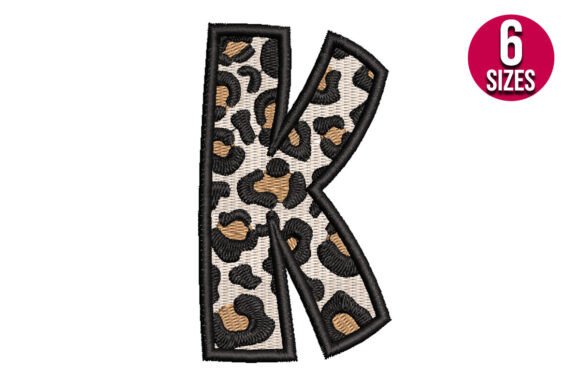
Leopard Print Alphabet Font Letter K
Ulasan Lengkap: Leopard Print Alphabet Font Letter K – Tambahkan Sentuhan Liar ke Desain Anda
Jika Anda mencari aksen yang berani dan penuh gaya untuk proyek kreatif Anda, Leopard Print Alphabet Font Letter K adalah pilihan tepat. Desain ini tidak hanya menawarkan motif leopard yang ikonik, tetapi juga fleksibilitas format file yang mendukung berbagai mesin bordir. Dari monogram elegan hingga hadiah personal, huruf K ini menambah unsur keunikan dan eksotisme pada setiap karya.
Keunggulan Utama Desain Leopard Print Letter K
- Motif Leopard Klasik: Gaya motif leopard yang terus populer, memikat mata dan menciptakan kesan “wild” yang tak tertandingi.
- Ideal untuk Monogram: Huruf K yang kuat dan jelas cocok untuk membuat monogram pribadi di pakaian, tas, atau aksesori.
- Gift Personalization: Cocok untuk hadiah terpersonal, misalnya kaos, hoodie, tas, dan aksesori lain yang ingin disesuaikan dengan gaya unik.
- Desain Efisien: Pattern yang dirancang dengan cermat mengoptimalkan pemakaian benang, sehingga mengurangi pemborosan dan biaya produksi.
Dengan Leopard Print Alphabet Font Letter K, proyek kreatif Anda tidak hanya akan menonjol, tetapi juga memancarkan keunikan yang tak terbandingkan. Mulai hari ini dan wujudkan karya yang memukau dengan sentuhan “wild” yang elegan!